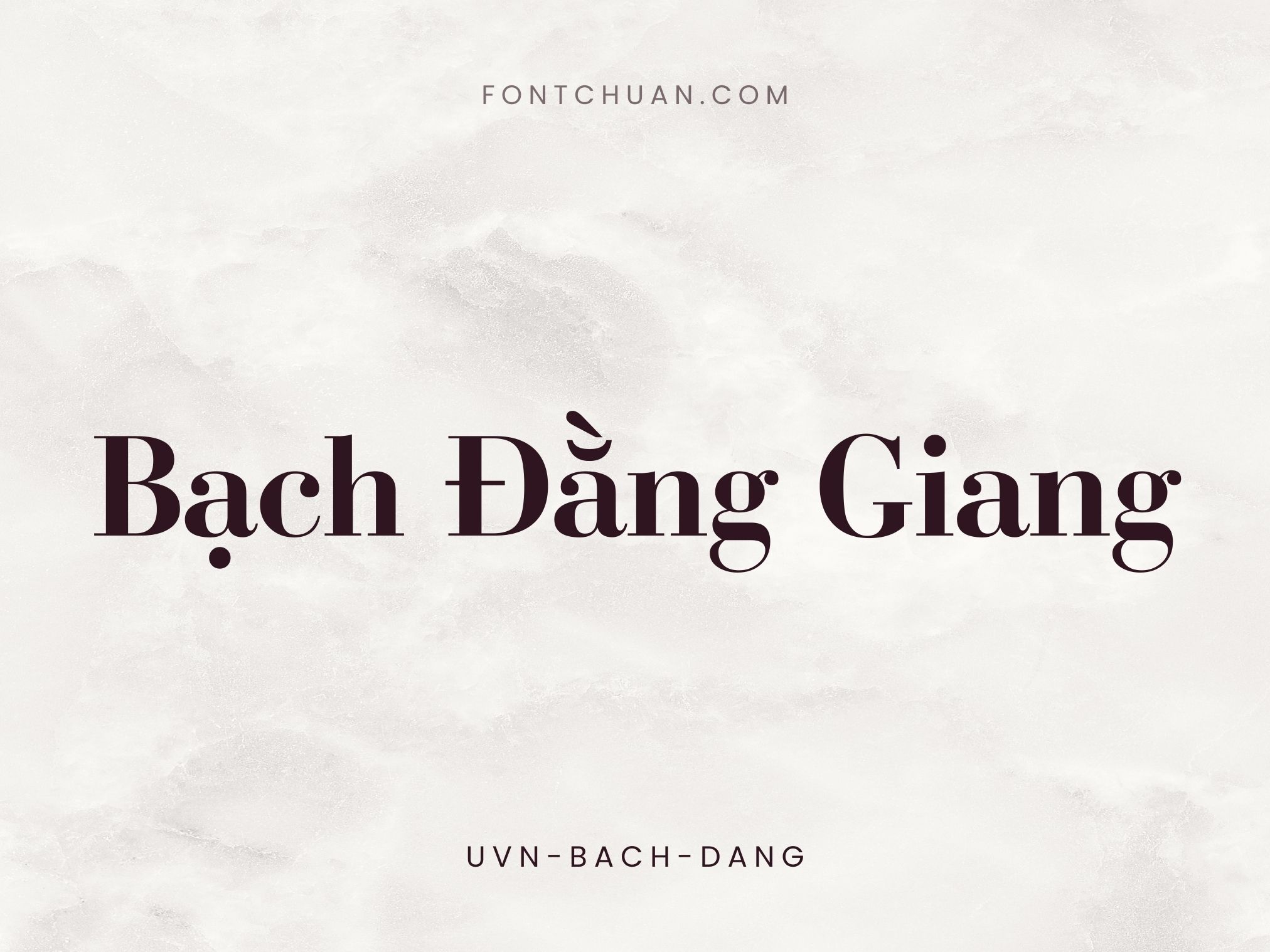
Font UVN Bach Dang Việt Hóa
UVN Bach Dang là một kiểu chữ serif được thiết kế với các đường nét thanh mảnh và tinh tế, mang đến vẻ đẹp cổ điển và trang nhã. Font này chỉ được sưu tầm và đăng bởi thành viên của Font Chuẩn.
UVN Bach Dang có cấu trúc chữ với các nét mảnh mai và chân chữ rõ ràng, tạo nên sự thanh lịch và dễ đọc. Font này phù hợp cho các ứng dụng như thiết kế thiệp mời, sách báo, tạp chí và các ấn phẩm in ấn yêu cầu sự trang trọng và cổ điển. Các ngành nghề như quảng cáo, giáo dục, công nghệ và bất động sản có thể tận dụng UVN Bach Dang để tạo điểm nhấn độc đáo trong thiết kế.